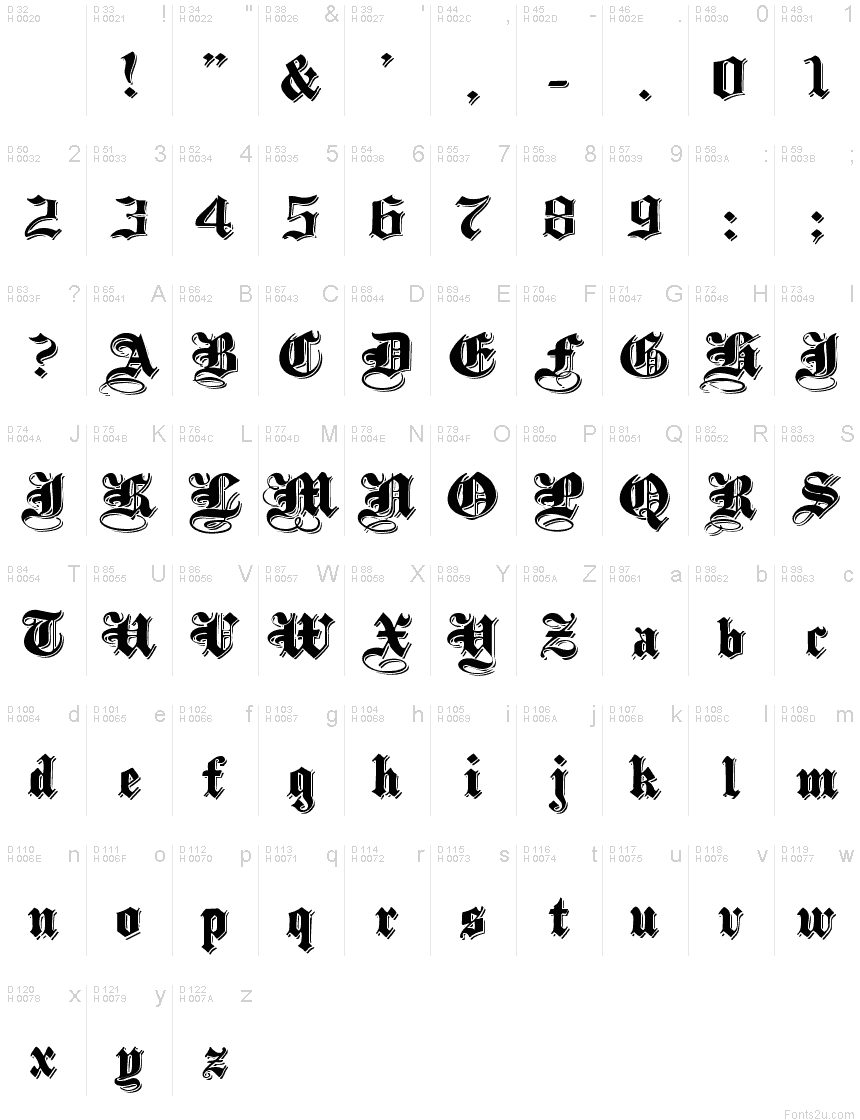
ShadowedBlackWide Normal
Shadowed Black Wide od ShadowedBlack je bezplatné blackletter písmo s nádechem středověkých novin. Písmena jsou hustá a ostře řezaná, ale skutečným lákadlem je vysazený stín, který tahům dodává hloubku jako u tištěného razítka, zatímco zdobené křivky brání tomu, aby písmo působilo ztuhle.
Hodí se na plakáty, přebaly alb, branding hospod, grafiku inspirovanou tetováním i titulní karty – všude tam, kde potřebujete historickou váhu, ale nechcete působit příliš obřadně. Použijte ho na krátké nadpisy, loga, úvody kapitol nebo monogramy. Stínování udělá většinu vizuální práce a dodá i několika málo znakům vytesaný, heraldický vzhled.